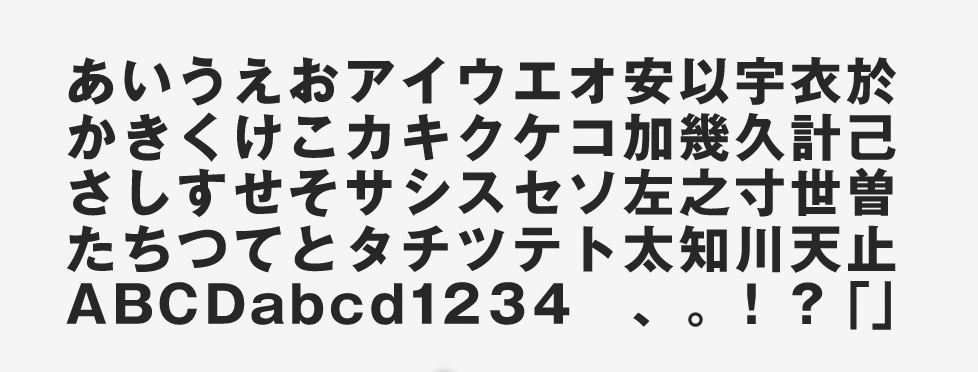
「ゴシックMB101」について
ゴシックMB101は、どっしりとした風格があるフォントです。写植用の見出ゴシック体MB101(※1)の流れを引き継いでおり、特に出版や広告の分野で定番の書体として親しまれています。主にタイトルやキャッチコピーなどに用いると効果的で、細いウエイトであれば本文組みなどにも対応。肉声の雰囲気やメッセージ性を感じさせやすいことも特徴です。
「ゴシックMB101」の特徴
骨格がしっかりとしているため、骨太で安心感・信頼感があります。ハネやハライの先端まで力強さを感じさせるフォントです。各エレメントでは手書きの雰囲気も多少残されており、幾何学的すぎない造形で “流れ” を感じさせます。
字面が大きい書体は一般的には横組みに適していますが、ゴシックMB101は縦組みでも違和感なく使用できます。また、特に堂々とした力強いインパクトを出したい場面では最適なフォントと言えるでしょう。
作例は、メッセージ性を強調させることが必要な交通安全週間の垂れ幕です。ゴシックMB101は、ハネ、ハライの部分のディテールによって、新ゴにはないクラシカルな印象があります。「ドン!」と説得力を出したいときに使うと効果てきめんです。